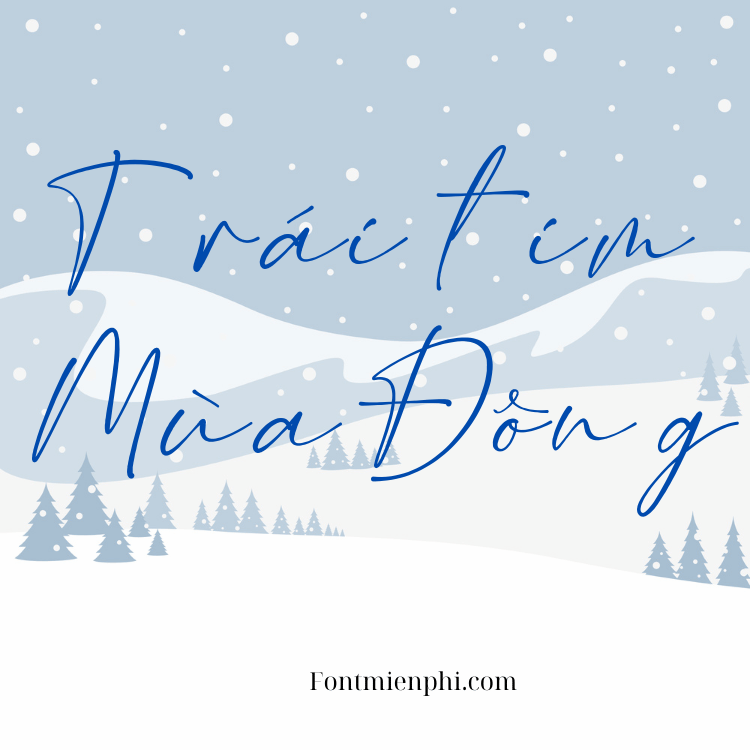
Việt hóa font LNTH Right Here – Bộ phông chữ hiện đại và sáng tạo cho thiết kế
Giới thiệu về dự án Việt hóa font LNTH Right Here
Trong thế giới đồ họa hiện nay, việc tìm kiếm một Font Miễn Phí chất lượng luôn là ưu tiên hàng đầu của các nhà thiết kế trẻ. Bộ Việt hóa font LNTH Right Here được ra đời nhằm đáp ứng nhu cầu sử dụng phông chữ viết tay tự nhiên nhưng vẫn giữ được sự chỉn chu. Đây là một phiên bản đặc biệt giúp người dùng Việt Nam dễ dàng thể hiện nội dung mà không lo lỗi dấu hoặc thiếu ký tự đặc trưng trong tiếng Việt.
Đặc điểm nổi bật của phông chữ
LNTH Right Here sở hữu những đường nét thanh mảnh, uyển chuyển, mang lại cảm giác thân thiện và gần gũi. Khi thực hiện Việt hóa font LNTH Right Here, các chuyên gia đã tinh chỉnh kỹ lưỡng hệ thống dấu câu sao cho hài hòa nhất với cấu trúc chữ gốc. Điều này giúp bộ font trở nên hoàn hảo cho các dự án thiết kế thiệp mời, bìa sách hoặc các bài giảng sáng tạo trong môi trường giáo dục.
Ứng dụng thực tế của Việt hóa font LNTH Right Here
Bộ font này không chỉ giới hạn trong thiết kế chuyên nghiệp mà còn rất phù hợp với các bạn học sinh, sinh viên. Bạn có thể sử dụng Việt hóa font LNTH Right Here để trang trí bài thuyết trình, làm tiêu đề cho các báo cáo ngoại khóa hoặc tạo ra những tấm thiệp tri ân thầy cô đầy ý nghĩa. Sự linh hoạt trong phong cách giúp nó dễ dàng kết hợp với nhiều loại layout khác nhau từ cổ điển đến hiện đại.
Kết luận về bộ font chữ đẹp